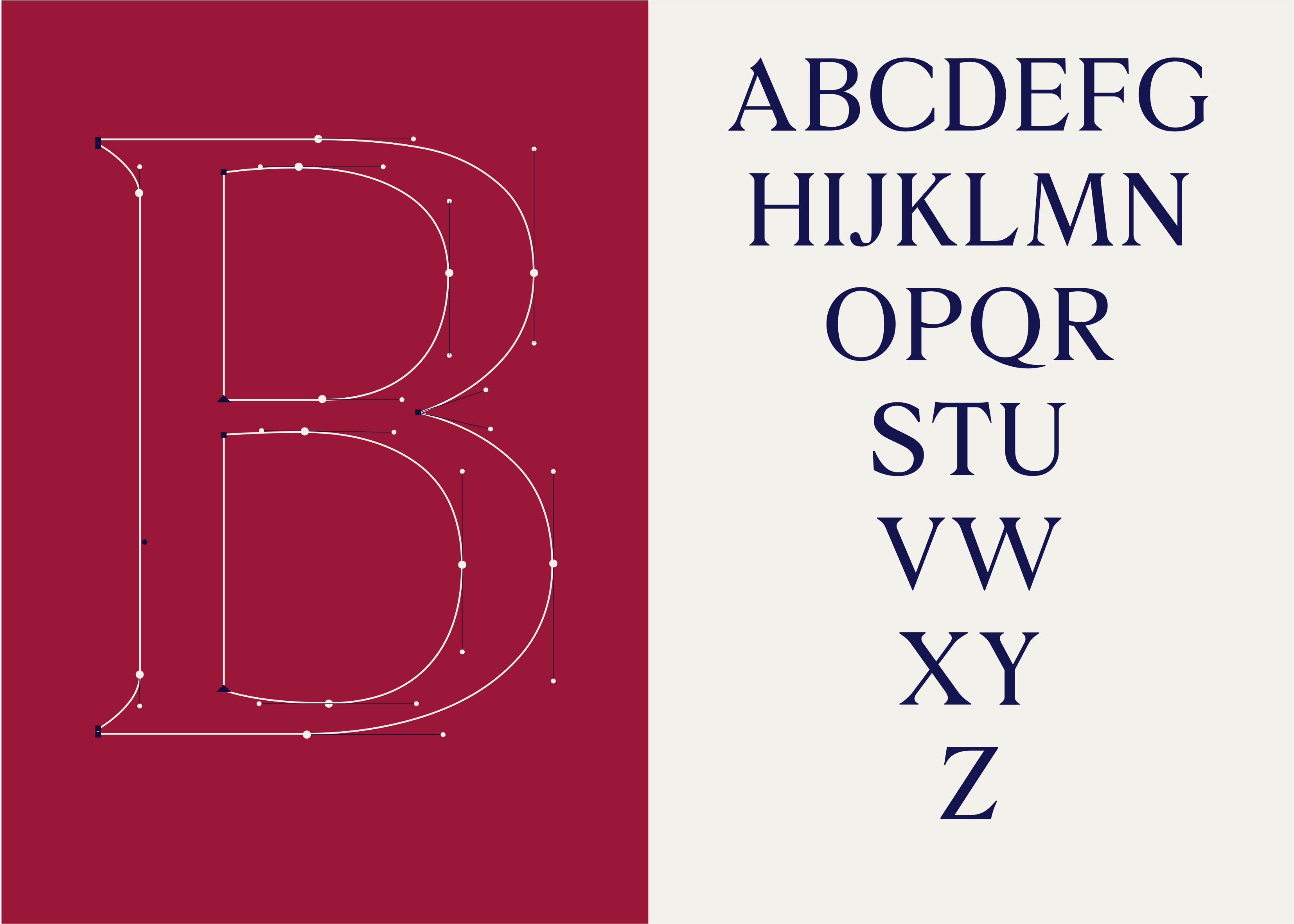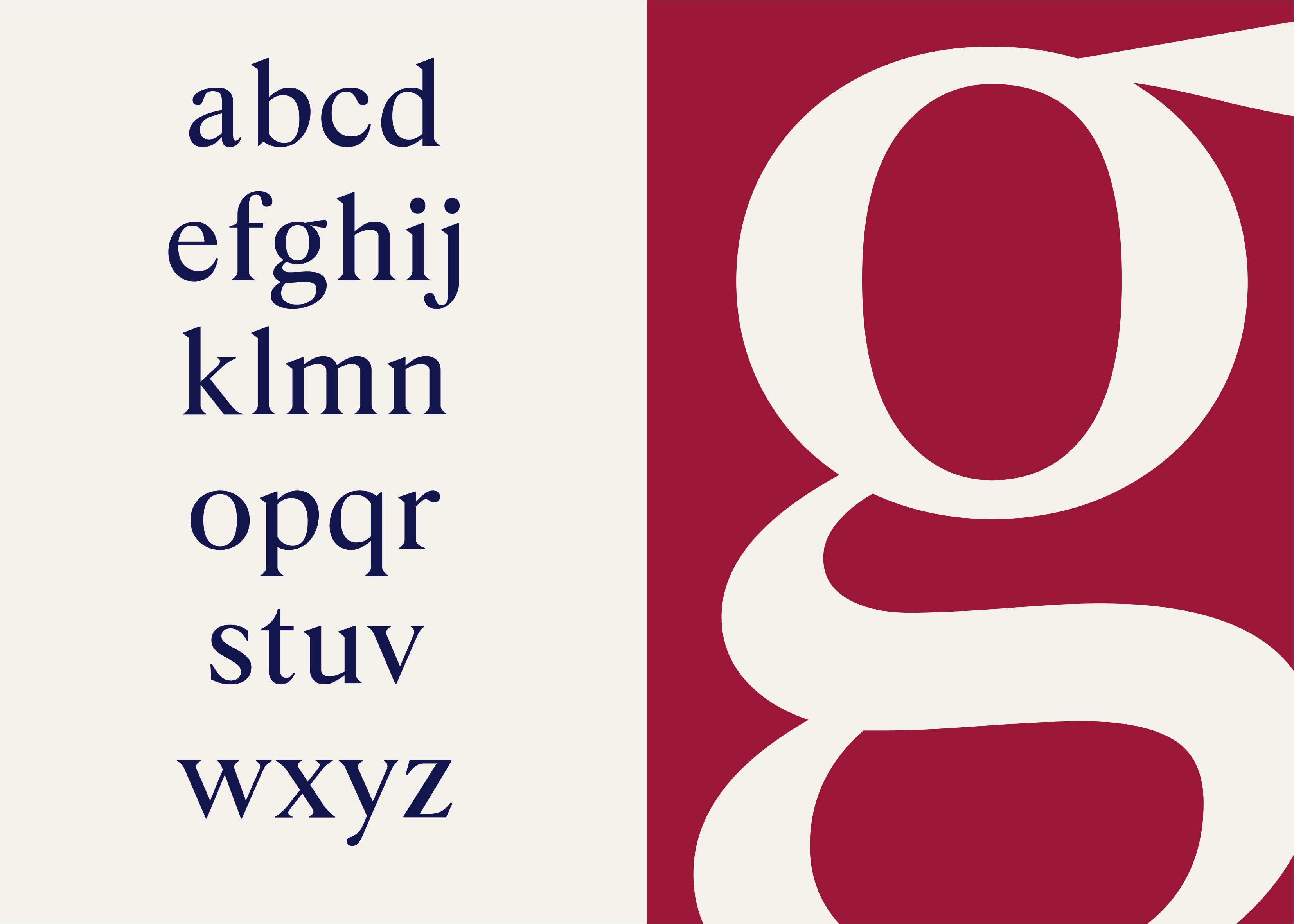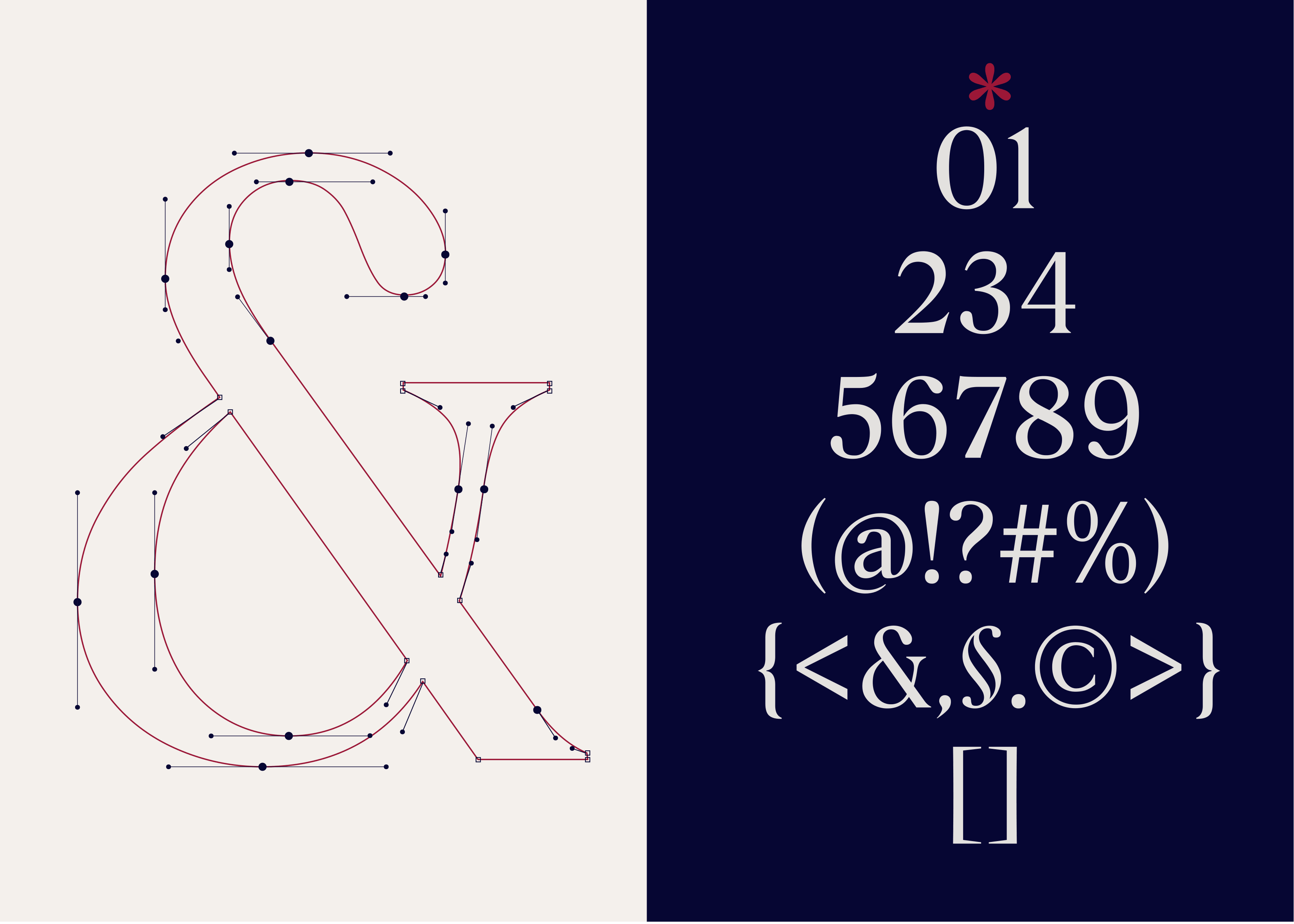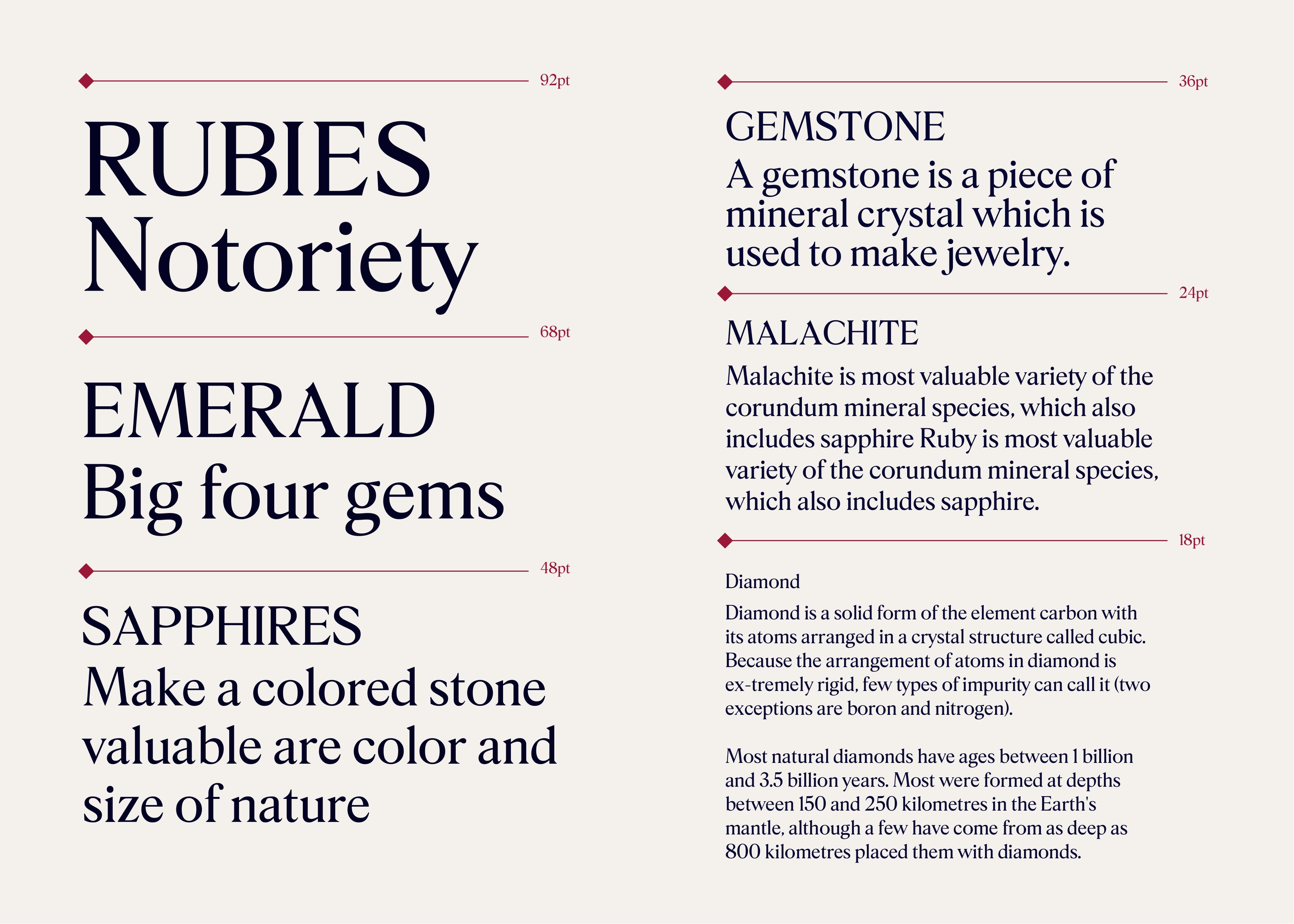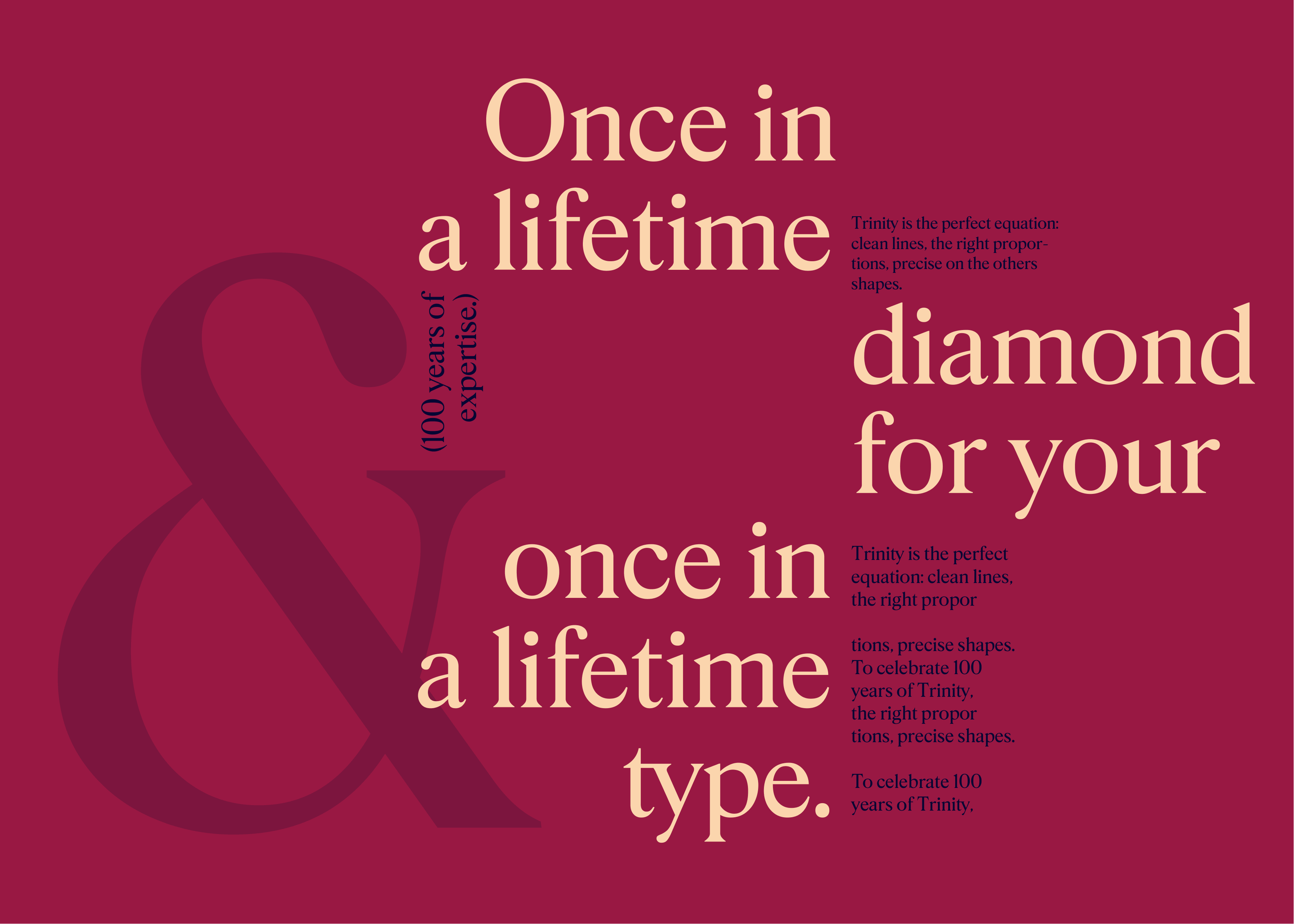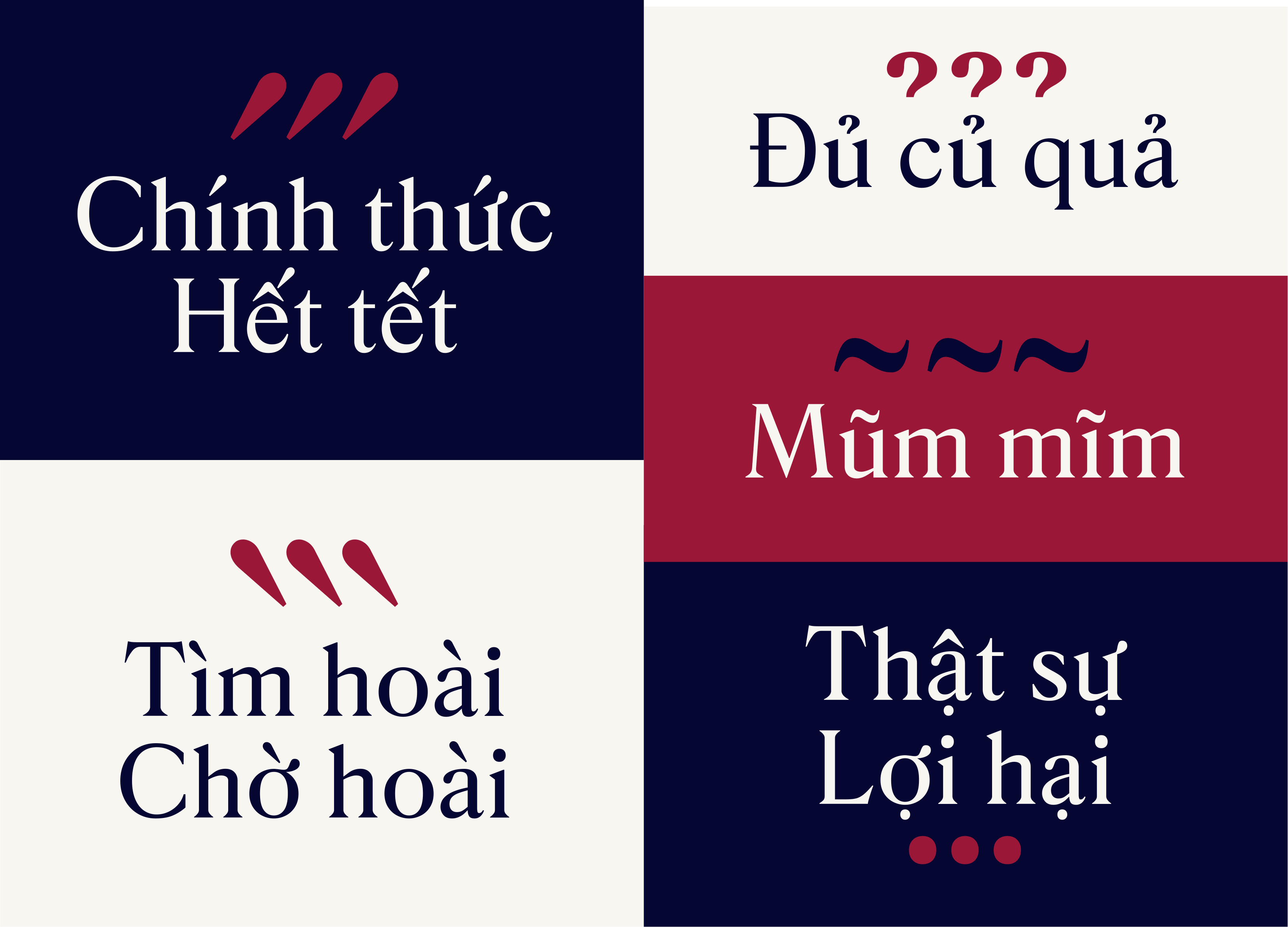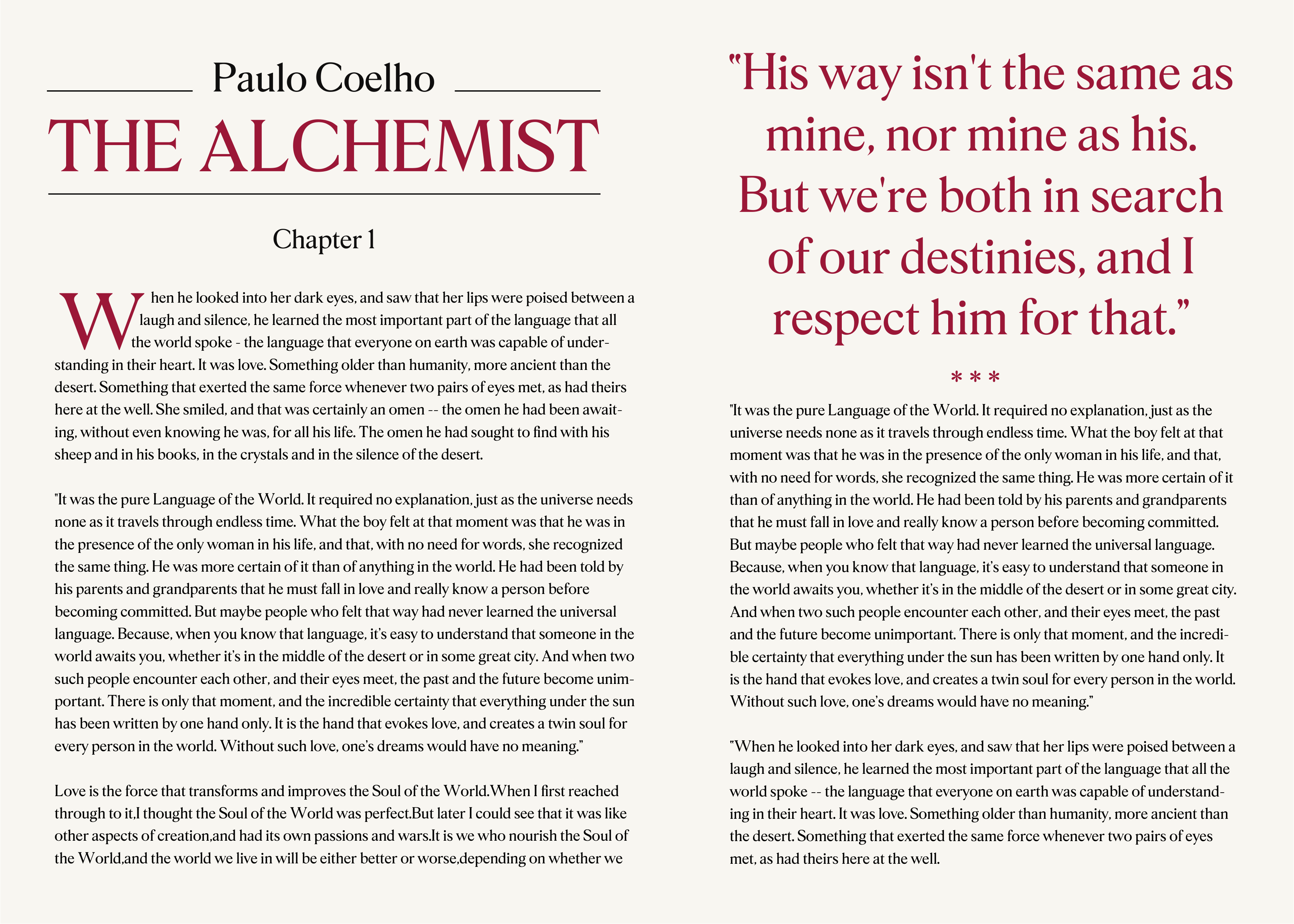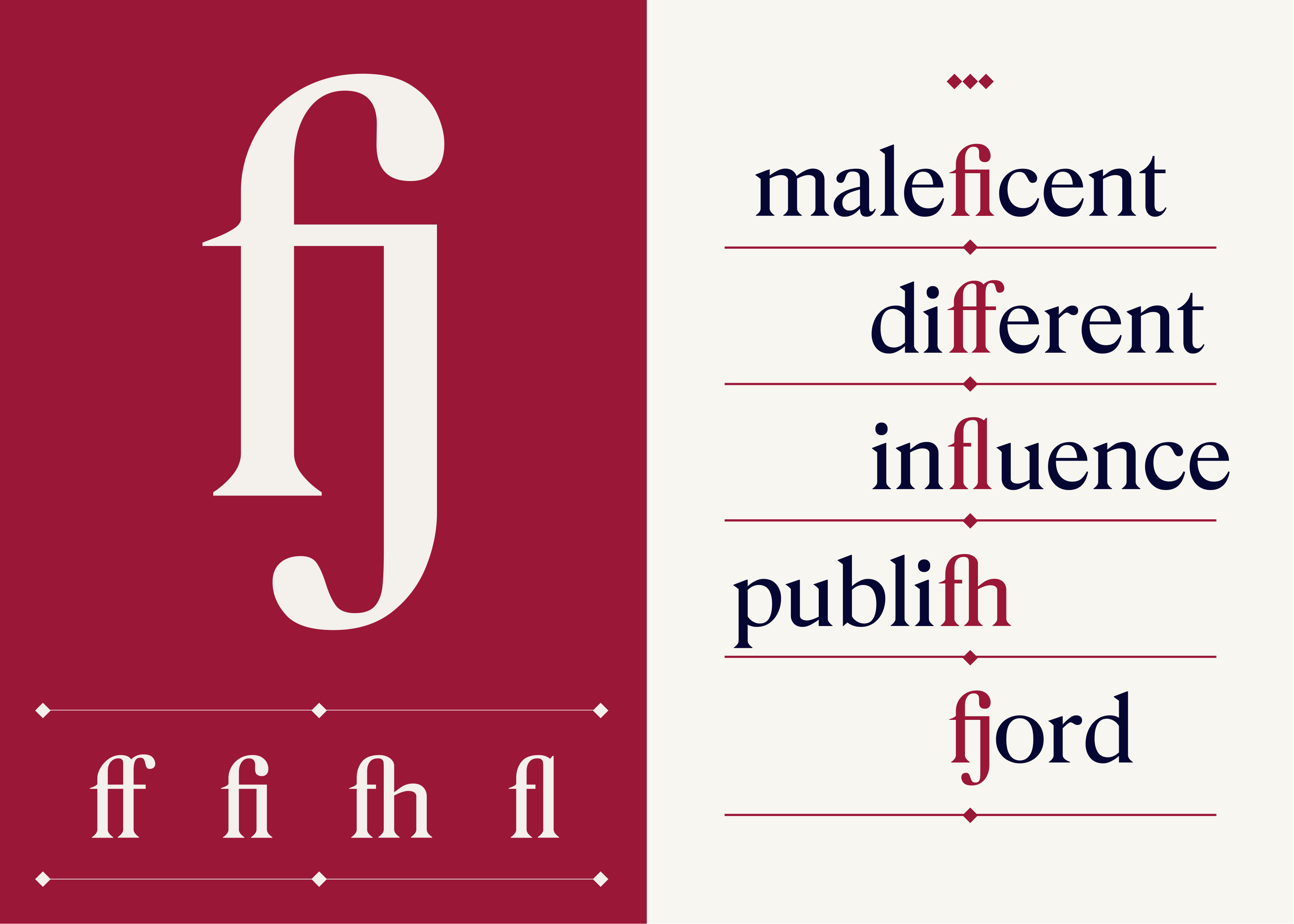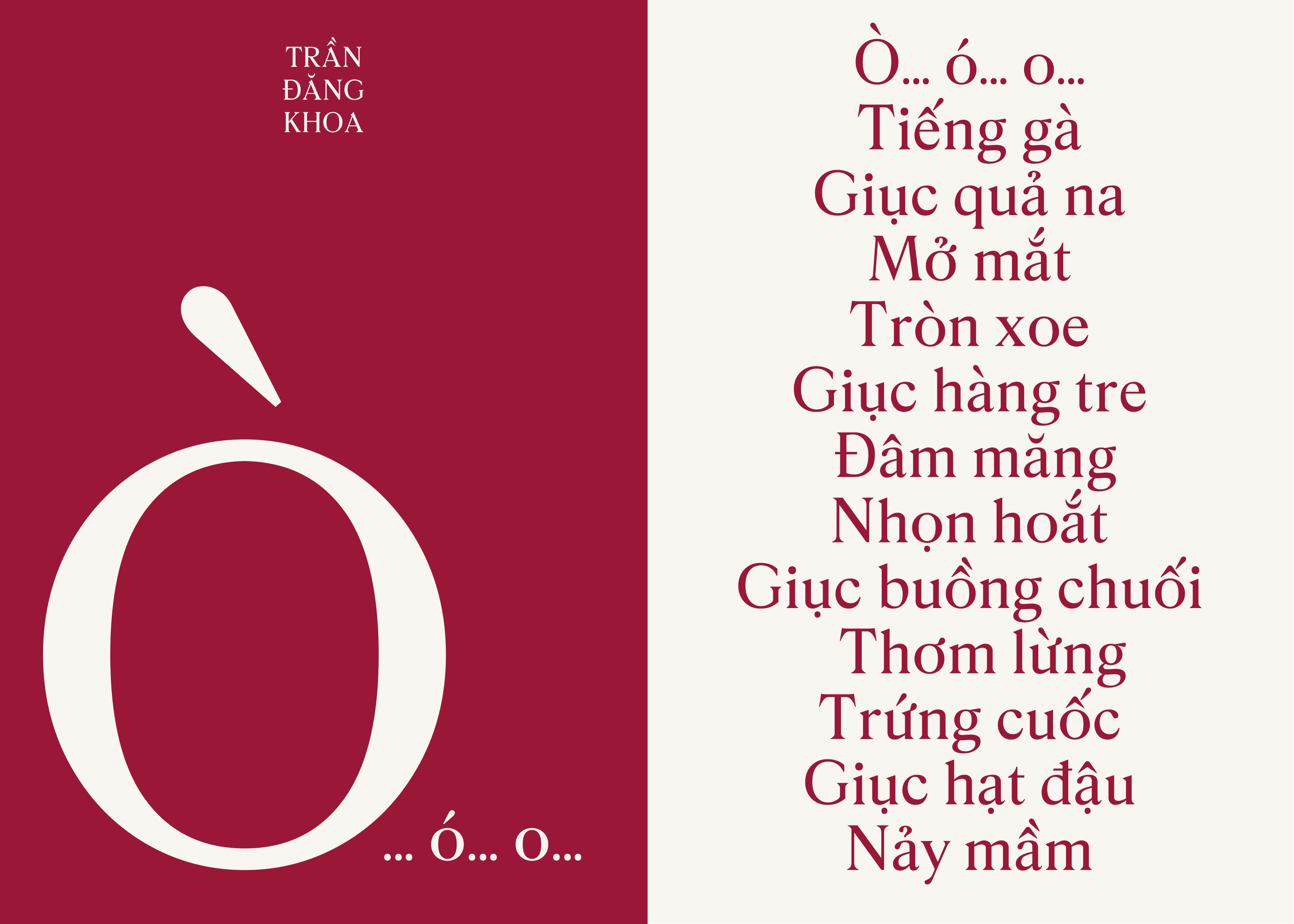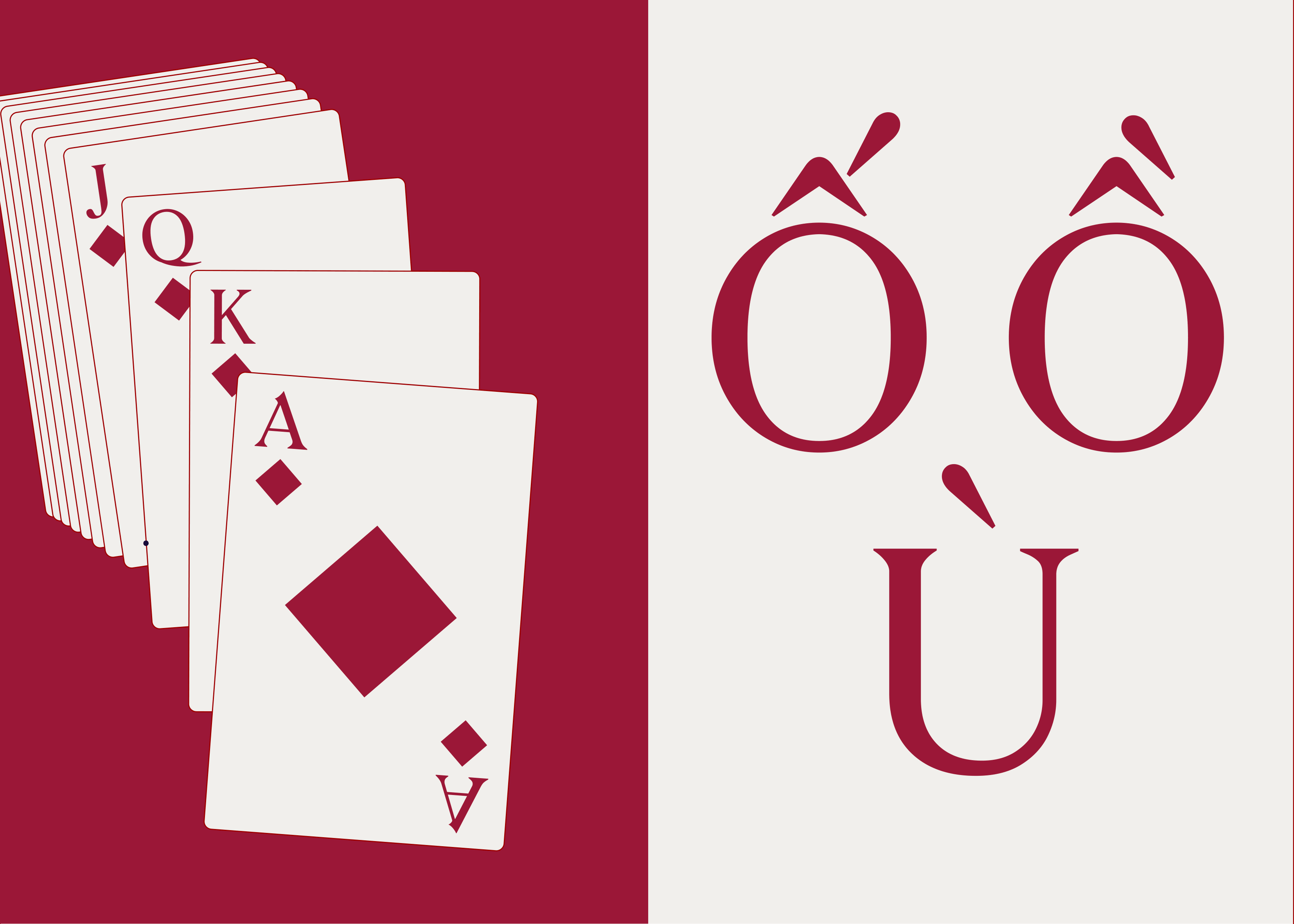
Choubau
Về Choubau: Lấy cảm hứng từ Elzevir Plantin, Chowbau lấp lánh những đoạn chuyển gấp sắc như kim cương. Cũng là Chowbau cứng cáp và thô ráp nhưng khi thành hình lại biến hoá mềm mại và uyển chuyển đến không ngờ.
Transitional Serif
Display
Choubau
Diamonds
Choubau
Shimmering Light
Choubau
Biến hóa
Choubau
Châu báu Ngọc ngà
Choubau
Elzevir Plantin is a typeface that emerged around 1905 and carried forward into the catalog of the Fonderie Typographique Francaise (FTF) after the 1921 merger.
Choubau
What makes Elzevir Plantin particularly fascinating is its true origin. The "Elzevir Plantin" italic issued by the Fonderie Typographique Francaise is actually the French cut of the German Romische Antiqua Cursiv, a typeface which predates De Vinne and many American eccentric Elzevir types. In other words, what the FTF marketed under a proudly French-sounding name, evoking both the Elzevir tradition and the legendary 16th-century Antwerp printer Christophe Plantin — was in fact rooted in a Germanic design tradition, quietly reinterpreted for the French market.